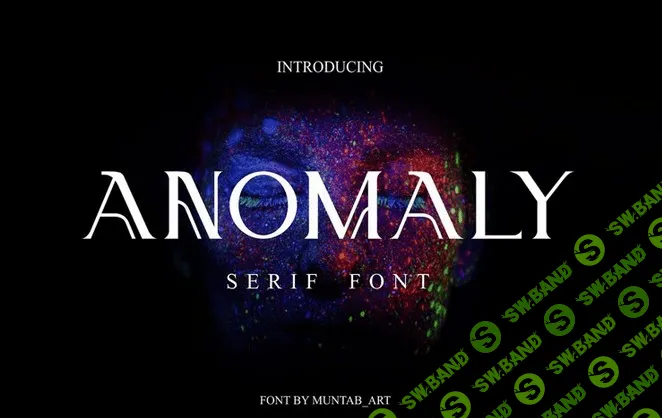
Название: Anomaly - Modern Serif Font
[Fontbundles] Anomaly - Modern Serif Font
Аномальные шрифты включают в себя заглавные буквы, цифры, большой диапазон знаков препинания.
Шрифт с засечками в современном стиле. Создан для плаката, веб-дизайна, брендинга, иллюстраций, значков и некоторых других работ.